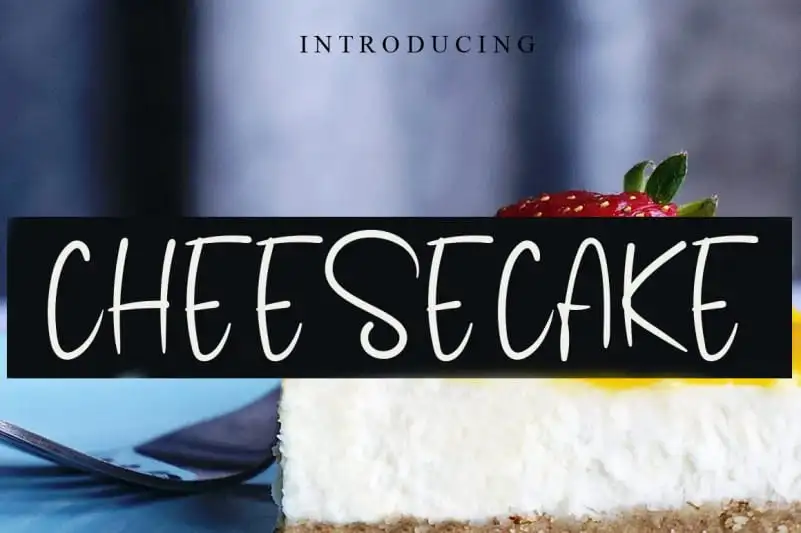
A fonte ‘Cheesecake Display Font’ é uma escolha perfeita para aqueles que buscam uma escrita handwritten fresca e agradável ao olho. Idealmente utilizada em designs de grandes volumes, esta fonte transmite um estilo natural e único, capaz de se encaixar em diversos ambientes gráficos sem perder sua identidade. O designer levincreative criou este recurso com base no gosto das receitas de cheesecake: leve, fresco e delicioso. O limite é apenas seu pensamento criativo, tornando a Cheesecake Display Font uma ótima escolha para criar um design memorável em sua próxima obra. Seja você um designer ou simplesmente alguém que aprecia boas ideias gráficas, este é um fonte onde todos os limites são desafios a serem ultrapassados.